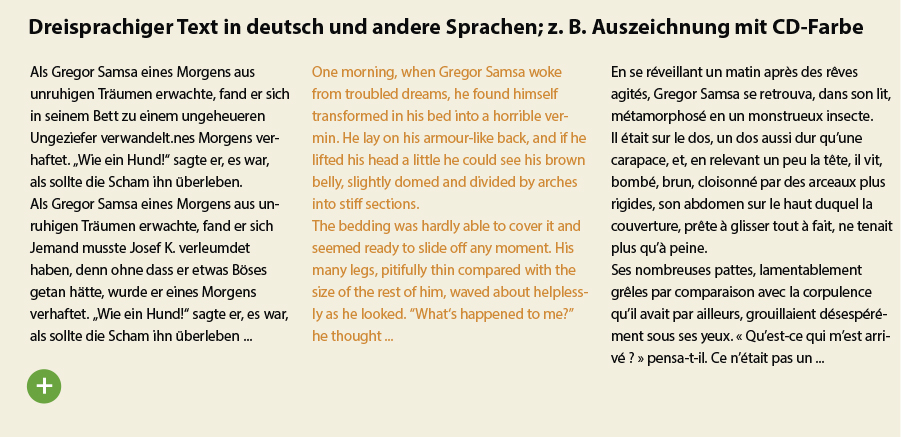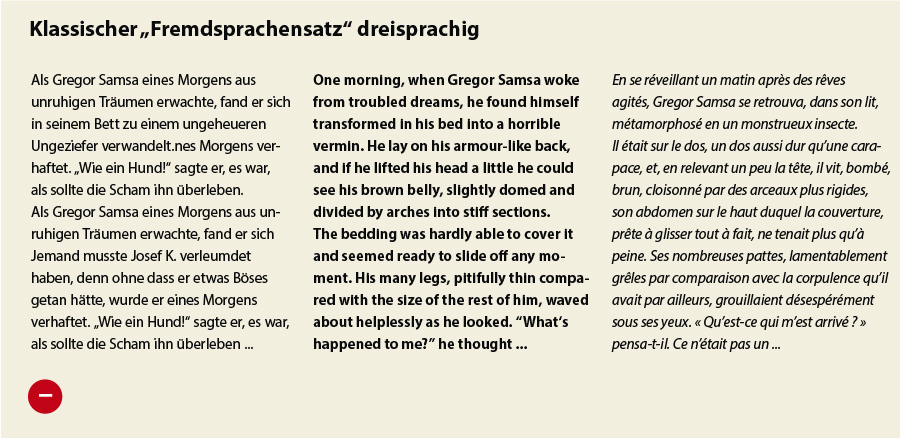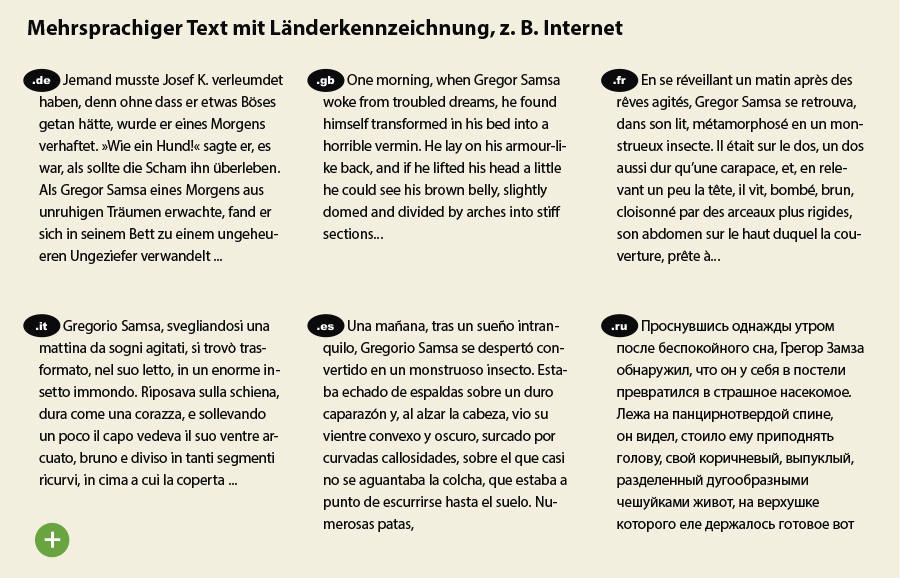
Mikrotypografie: Schriften auszeichnen – mehrsprachige Texte typografisch korrekt hervorheben
Fremdsprachensatz typografisch korrekt auszeichnen
In der Schriftklassifikation nach DIN 16518 ist der Begriff der Schriftenklasse XI „Fremde Schriften“ seit einiger Zeit überholt. Die Klasse heißt jetzt „Schriften anderer Kulturkreise“. In Sachen „Political Correctness“ mag das der eine oder andere vielleicht etwas übertrieben finden. Doch es zeigt, dass man auch in der Typografie in so manches Fettnäpfchen treten kann – zum Beispiel in der Auszeichnung von Texten. Wieso, weshalb, warum und wie Sie sich typografisch-politisch korrekt verhalten, darum geht es in diesem Blogbeitrag.
Unbeabsichtigte Wertung durch Auszeichnungen
Nehmen wir mal an, Sie gestalten eine Unternehmensbroschüre in drei Sprachen: Deutsch, Englisch und Französisch. Um die drei Sprachen voneinander abzugrenzen, zeichnen Sie die Texte unterschiedlich aus – in Regular, Bold und Italic. Durch die Auszeichnungen kann es zu einer „unbeabsichtigten Wertung“ kommen, weil sie zum Beispiel von Lesern anderer Nationen falsch verstanden werden, was vom Absender natürlich nicht gewollt ist. In meinen beiden Workshops zu den Themen Typografie und Layouttechnik sowie Detailtypografie im Kommunikationsdesign kommt deshalb regelmäßig die Frage auf, wie man sich bei der Kennzeichnung von Texten verschiedener Sprachen typografisch korrekt verhält. Statt die Deutschen „normal“, die Briten „fett“ und die Franzosen „schräg“ zu machen wie im folgenden Beispielen, empfehle ich zwei Alternativen.
Keine gute Lösung: Fremdsprachensatz in Regular, Bold und Italic auszeichnen.
Alternative #1: Auszeichnung von Text in einer Corporate Color
Das Beispiel unten zeigt den goldenen Mittelweg, nämlich eine Auszeichnung in einer Corporate Color, die abwechselnd angewendet wird. Das sorgt für Spannung im Layout, ohne „wertend“ zu sein. Wenn Sie die Textblöcke in Schwarz einfach nur nebeneinander stellen, geht die Orientierung zwar ebenfalls nicht verloren. Das Layout läuft jedoch Gefahr, monoton auszusehen. Das Beispiel oben, ein Ausschnitt aus dem Buch „Porsche Sounds“ von Dieter Landenberger, geht ebenfalls sehr geschickt mit einer zweiten Farbe um.
Fremdsprachensatz typografisch korrekt auszeichnen mit Farben
Alternative #2: Kennzeichnung von Text durch Orientierungsmarken
Bei Verkaufsverpackungen oder Gebrauchsanweisungen, die häufig mit mehr als sechs verschiedenen Sprachen versehen werden, geben Landeskennzeichnungen eine gute Orientierung. Die Orientierungsmarken können Sie zusätzlich in einer Corporate Color auszeichnen. In der Reihenfolge halte ich mich in der Regel entweder an die Verbreitung der jeweiligen Sprachen. Bei mehr als sechs Sprachen sortiere ich nach dem Alphabet.
Fremdsprachensatz typografisch korrekt auszeichnen mit Länderkennzeichen
Farbliche Hervorhebung in Printobjekten
Hier ein paar sehr schöne Beispiele aus dem Corporate Design einer Hotelkette, die kreativ mit einer Corporate Color zur Auszeichnung des zweisprachigen Textes umgeht:
Zusammenfassung: Text anderer Sprachen typografisch richtig auszeichnen
• Mehrsprachige Texte sollten nicht mit den Möglichkeiten einer Schriftfamilie, zum Beispiel Regular, Bold oder Italic, ausgezeichnet werden, da sie als „wertend“ missverstanden werden können
• Werden mehrsprachige Texte in Broschüren gar nicht ausgezeichnet, sollten diese in Blöcken nebeneinander stehen
• Fortlaufende mehrsprachige Texte können Sie wechselnd in einer Farbe – zum Beispiel einer Corporate Color – auszeichnen. Das Layout wirkt dadurch oft spannender
• Texte in vielen anderen Sprachen – zum Beispiel für Verkaufsverpackungen oder Gebrauchsanweisungen – können zur besseren Orientierung mit Länderkennzeichen versehen werden
• Die Reihenfolge der Texte anderer Sprachen sollte bei einer deutschen Publikation nach Deutsch in der Häufigkeit der gesprochenen Sprache erfolgen, oder ab 6 Sprachen alphabetisch